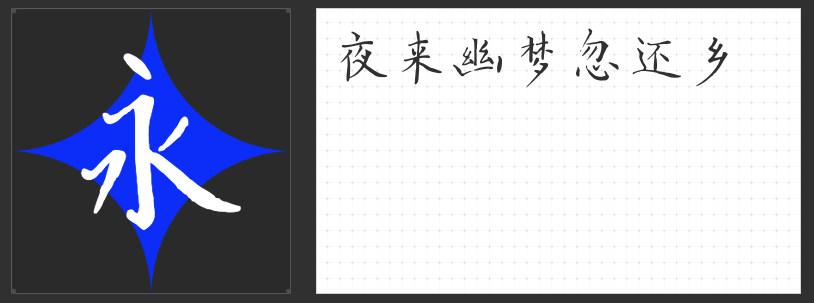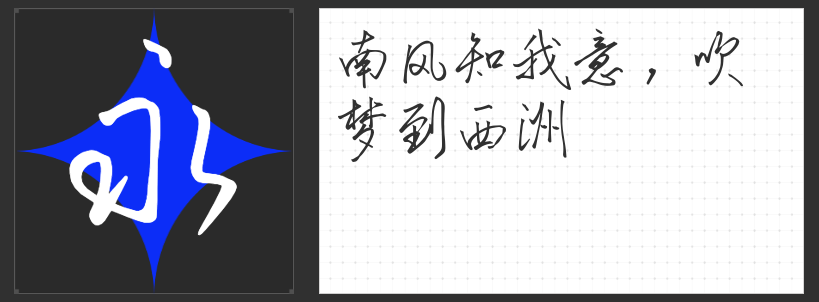
四款古风字体推荐:以笔墨勾勒影视世界的东方美学
在古风影视设计中,字体不仅是信息传递的载体,更是营造氛围、传递文化底蕴的关键元素。以下四款字体各具特色,以行书之洒脱、楷书之端庄、行楷之灵动,为影视视觉注入典雅韵味。
一、安景臣行书速成版
安景臣行书速成版以传统行书为根基,化繁为简,突破传统书写法则的束缚,既保留行书飘逸流畅的笔意,又简化笔画结构,提升书写效率。其字形舒展而不失法度,笔画间呼应自然,如行云流水般一气呵成。适用于影视字幕、片头题字等场景,既能传递古风意境,又符合现代观众对简洁美学的追求,尤其适合需要快速呈现的动态画面。
二、云书法朴拙小楷
云书法朴拙小楷融合王羲之的圆润含蓄与欧阳询的严谨结体,以骨力遒劲、温润灵动的笔触,重塑楷书的古典魅力。其字形端庄中见灵动,笔画粗细有致,既有碑刻的古朴厚重,又不失手写的自然韵味。适用于影视海报、宣传物料等需要体现文化底蕴的场景,尤其适合历史题材或文人叙事类作品,以规整之美传递岁月沉淀的质感。
三、造字侠醉春风简繁 苍劲
造字侠醉春风简繁以自由率真为魂,字形周正而不失灵动,笔画圆润饱满,粗细过渡自然,如春风拂面般洒脱不羁。其独特的字形风貌既保留传统书法的韵律感,又融入现代设计的简洁美学,适合影视片头、场景标题等需要突出视觉张力的场景,以苍劲笔触勾勒出江湖侠气或山水意境。
四、云书法玉兰行楷体
云书法玉兰行楷体以毛笔书写的自然流畅为基调,字形匀称而主笔画突出,块面感与层次感并存。其笔画牵丝连带,书写连贯,既有行书的洒脱飘逸,又具楷书的端庄稳重。适用于影视封面、文创设计等场景,以刚柔并济的笔触传递东方美学的韵律感,尤其适合古装仙侠或宫廷题材,以气韵生动诠释角色情感与故事氛围。
这四款字体以不同的笔墨语言,共同构建出古风影视设计的东方美学体系,为视觉呈现注入文化灵魂。